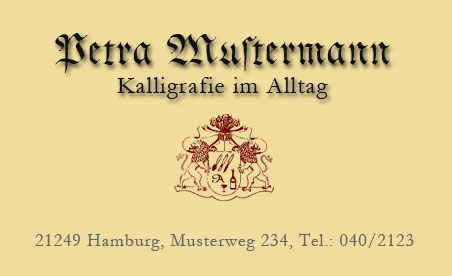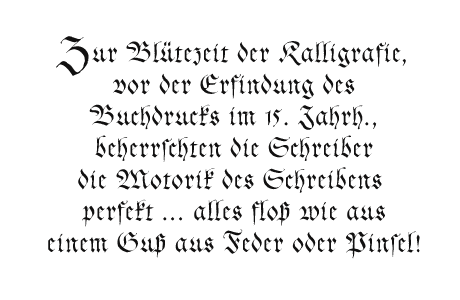
Schwungfraktur
Um sich von den glatt geschnittenen Frakturen abzusetzen, hier die Digitalisierung einer handgeschriebenen Fraktur, bei der die kleinen Unregelmäßigkeiten der Handschrift nicht beseitigt sind.
Der Font kann damit auch als Vorlage zu eigenen kalligrafischen Versuchen benutzt werden - viel Spaß damit
There are a lot of well cut blackletter types around.
Here a digitalised handwritten Font with all the little itches that happen while writing with a pen.
The font may be used to start own handwriting - have fun
Hier ein Beispiel für die Anwendung dieser Schrift,
sie eignet sich besonders für Überschriften
Das lange s ist - wie üblich -
über das Nummernzeichen '#' auf der Tastatur erreichbar